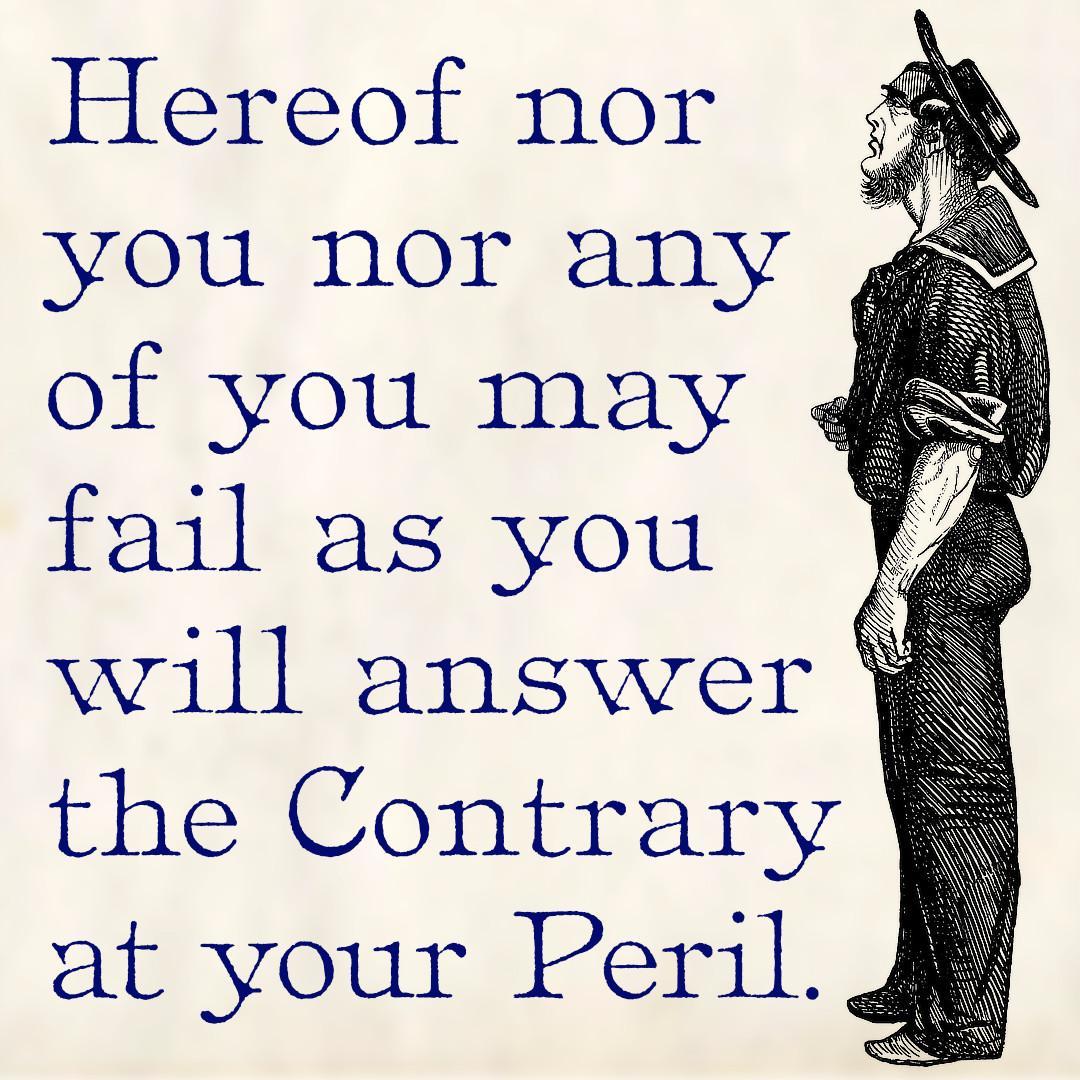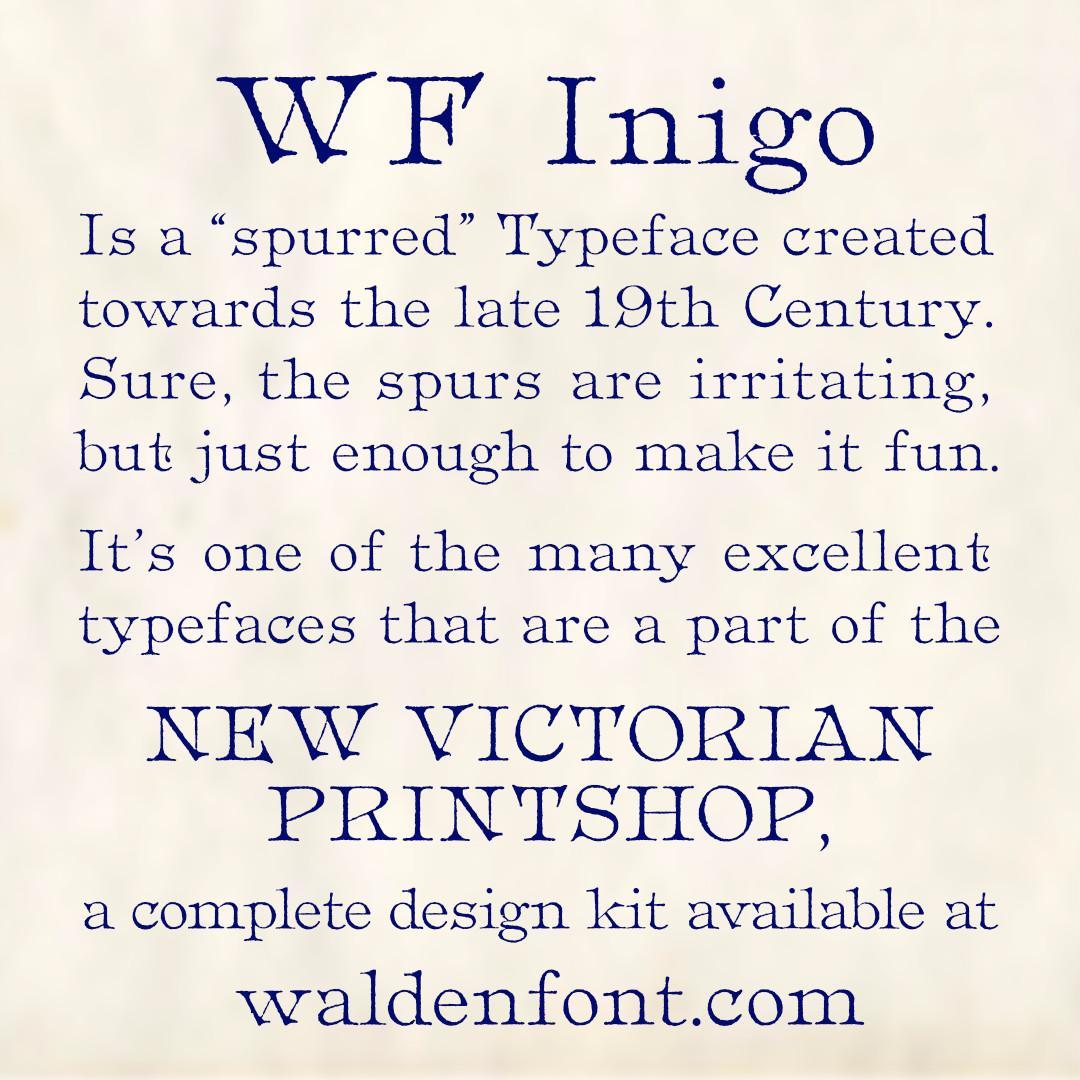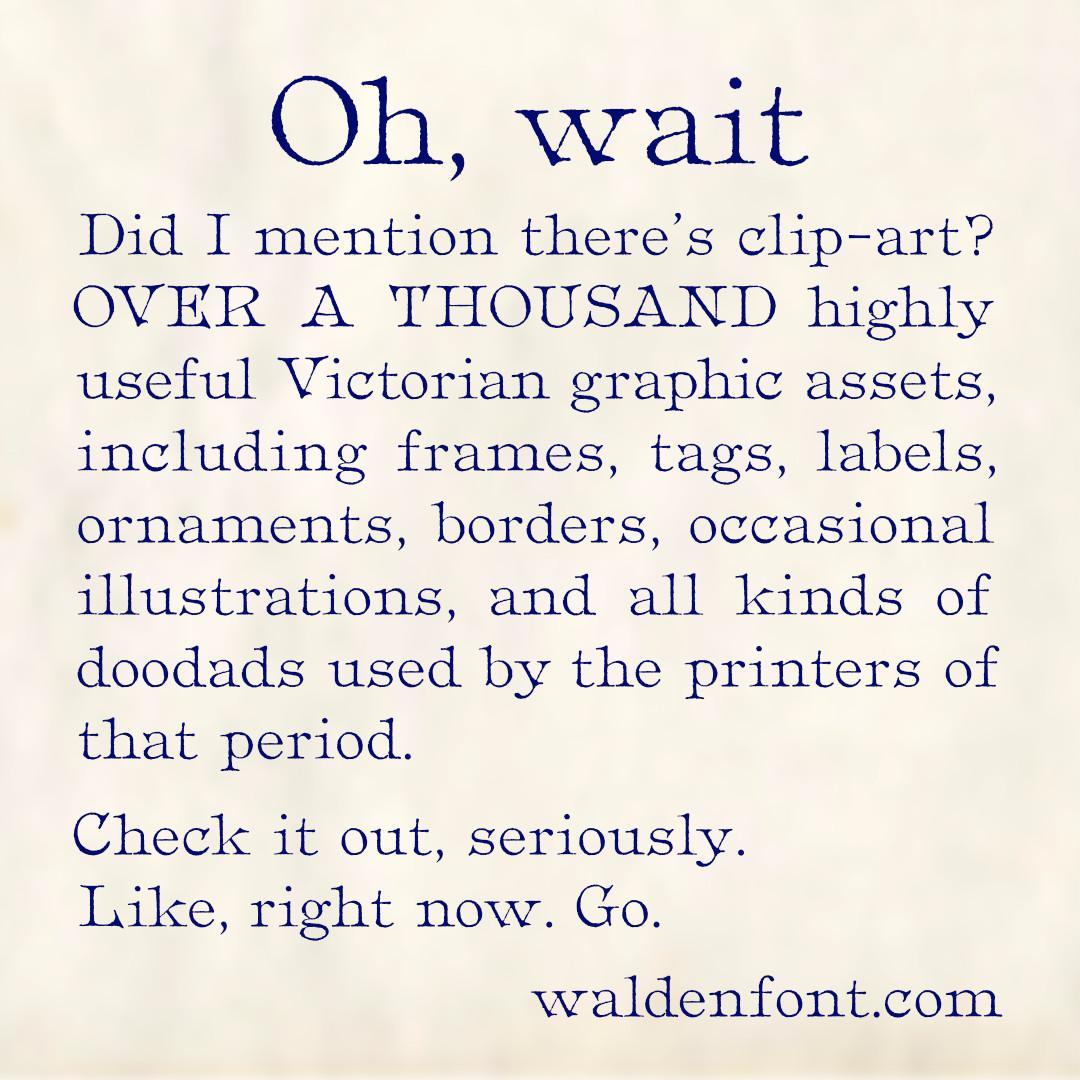
Ja, konsequent inkonsistent. :-P
Ich würde sie vermutlich aus diesem Grund auch nicht einsetzen – allenfalls in einem Logo. Man bleibt zu sehr an den Eigenheiten kleben.
Wieso macht man sowas?
Solche Dinge funktionieren m. E. nur in Schauschriften, und auch da nur wenn man die Idee konsequent einsetzt, damit sie ein erwarteter Bestandteil der Buchstaben ist. Diese Sporne sind recht unglücklich gewählt, denn bei den Großbuchstaben passt es wirklich nur bei J, und bei U (aber nur rechts). Zudem sind die Sporne viel zu klein um als solche erkennbar zu sein. Auch hätte ich sie bei den Gemeinen verwendet. Aber wie gesagt, bei einer Brotschrift sollte man Schnörkel tunlichst weglassen.
Ansonsten gefallen mir Sporne aller Art 🙂